字游工房の書体設計士 鳥海修氏による待望の新刊『明朝体の教室 ~日本で150年の歴史を持つ明朝体はどのようにデザインされているのか~』発売記念!直筆サイン本が当たるフォロー&リポストキャンペーンを実施
モリサワは、関連会社である有限会社字游工房の書体設計士 鳥海修氏による書籍「明朝体の教室 ~日本で150年の歴史を持つ明朝体はどのようにデザインされているのか~」が2024年1月10日にBook&Designから発売されたことを記念して、直筆サイン本をプレゼントするフォロー&リポストキャンペーンを実施した。
明朝体の教室 ~日本で150年の歴史を持つ明朝体はどのようにデザインされているのか~
書体デザインの第一人者である鳥海修氏が上梓した書籍「明朝体の教室 ~日本で150年の歴史を持つ明朝体はどのようにデザインされているのか~」は、制作手順から各書体の比較検討、文字の歴史まで、明朝体のすべてをわかりやすく解説している。
字游工房の游明朝体を基準にして、漢字、ひらがな、カタカナ、アルファベット、約物の順に文字デザインの特徴を説明しているほか、さまざまな明朝体と比較しながら明朝体の本質に迫る内容となる。
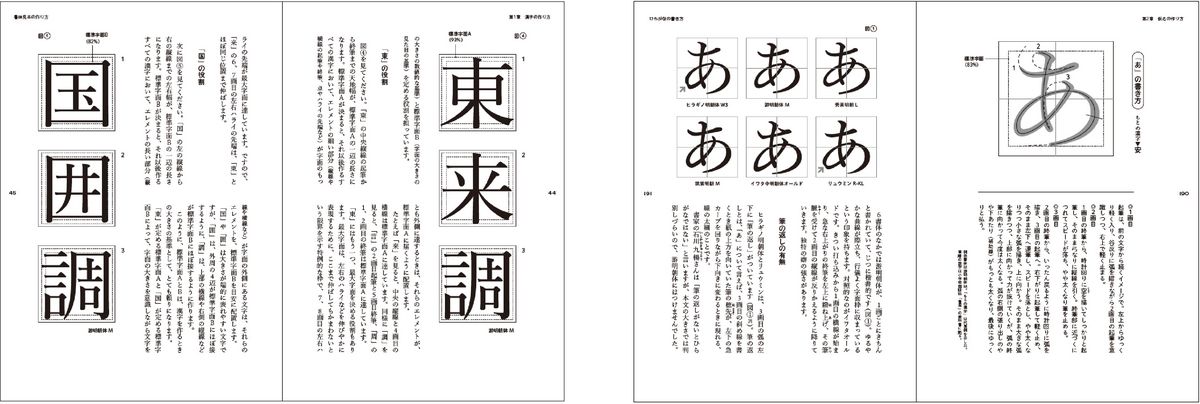
鳥海修Profile
書体設計士。1955年山形県生まれ。多摩美術大学卒業。79年写研入社。89年字游工房の設立に参加する。 ヒラギノシリーズ、こぶりなゴシック、游書体ライブラリーの游明朝体・游ゴシック体など、ベーシックな書体を中心に100以上の書体開発に携わる。 2002年佐藤敬之輔賞、05年グッドデザイン賞、08年東京TDCタイプデザイン賞を受賞。12年から「文字塾」を主宰し、現在は「松本文字塾」(長野県松本市)で明朝体の仮名の作り方を指導している。22年には個展「もじのうみ 水のような、空気のような活字」(京都dddギャラリー)を開催した。 著書に『文字を作る仕事』(晶文社、日本エッセイスト・クラブ賞受賞)、『本をつくる 書体設計、活版印刷、手製本――職人が手でつくる谷川俊太郎詩集』(河出書房新社、共著)がある。